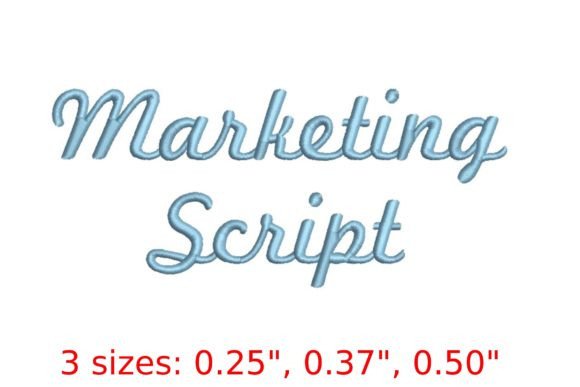
Marketing Script Embroidery Font
Nếu bạn đang tìm kiếm các tài nguyên chất lượng cao như Marketing Script Embroidery Font, gói cao cấp này là một lựa chọn tuyệt vời cho các dự án sáng tạo của bạn.
Được chế tác với độ chính xác cao, Marketing Script Embroidery Font cung cấp các vector sạch, kiểu chữ mượt mà và giấy phép thương mại để bạn yên tâm.
Cho dù bạn đang tạo sản phẩm POD (In theo yêu cầu), thiệp mời đám cưới hay đồ họa mạng xã hội, Marketing Script Embroidery Font đều là một sự lựa chọn lý tưởng.